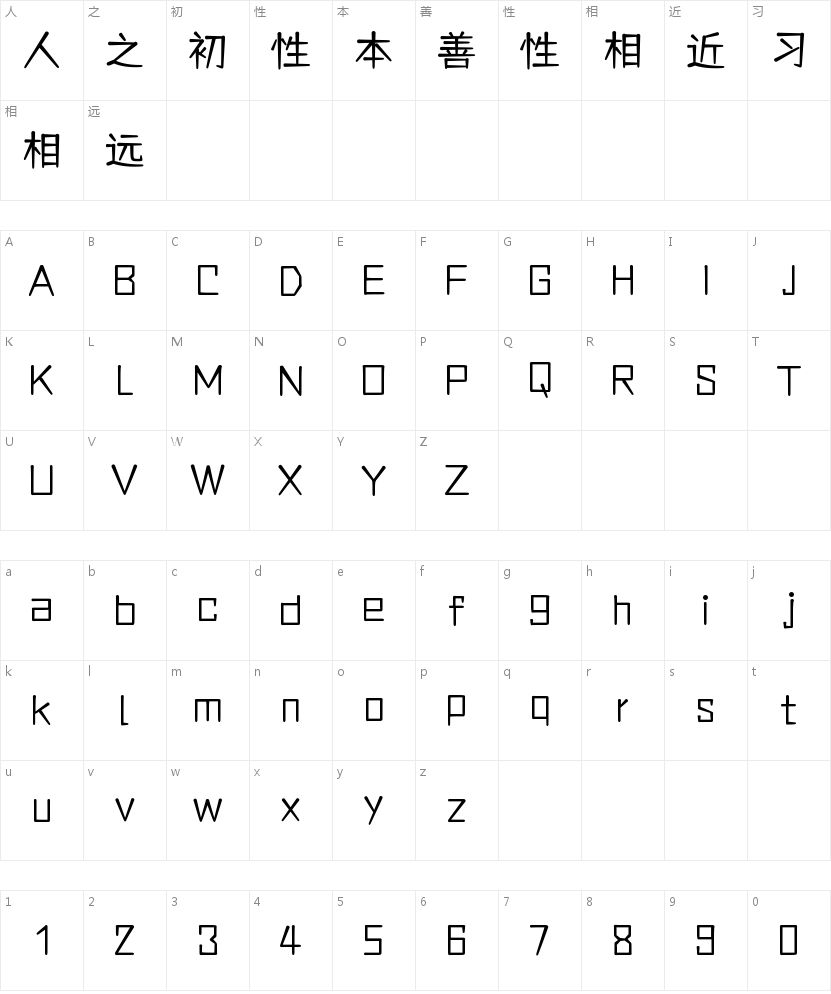
仓耳舒圆体
仓耳舒圆体是仓耳字库推出的一款免费字体,这种字体的设计灵感来源于苏轼的词“缺月向人舒窈窕”,让人联想到未圆满的月亮就像一个安静的美人,举止优雅。
仓耳舒圆体的独特之处在于其笔形设计,一端较粗一端较细,自然过渡,给人一种圆润饱满的感觉。这种字体在保持端庄的同时又不失几分慵懒,给人一种轻松愉悦的感受。此外,字形轮廓整体统一,使得这种字体在视觉上更具吸引力。
仓耳舒圆体家族拥有5个不同的字重,这些字体都经过精心设计,并可以免费商用。这种字体于2020年9月发布了第一版,受到了广泛的好评。
仓耳舒圆体的字数非常可观,它基于GB2312-80字符集汉字部分标准进行设计。这种TrueType格式字体共收容汉字6763个,同时还包括英文及标点等常用字符245个。这意味着这种字体可以广泛应用于各种不同的场景,无论是商业还是非商业用途都可以免费授权给全社会使用。
仓耳舒圆体效果预览